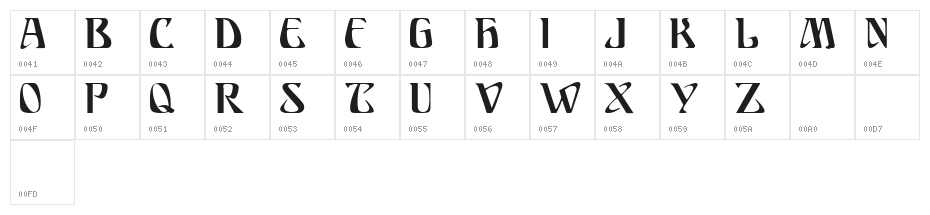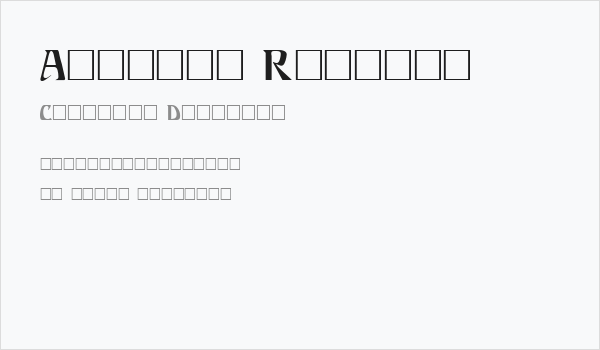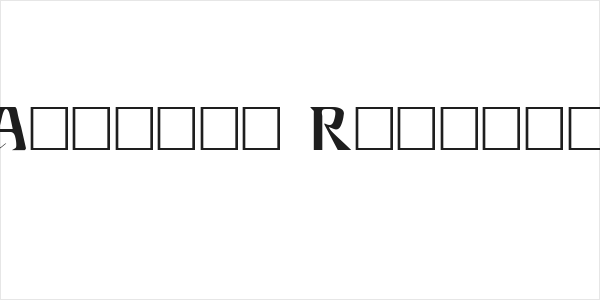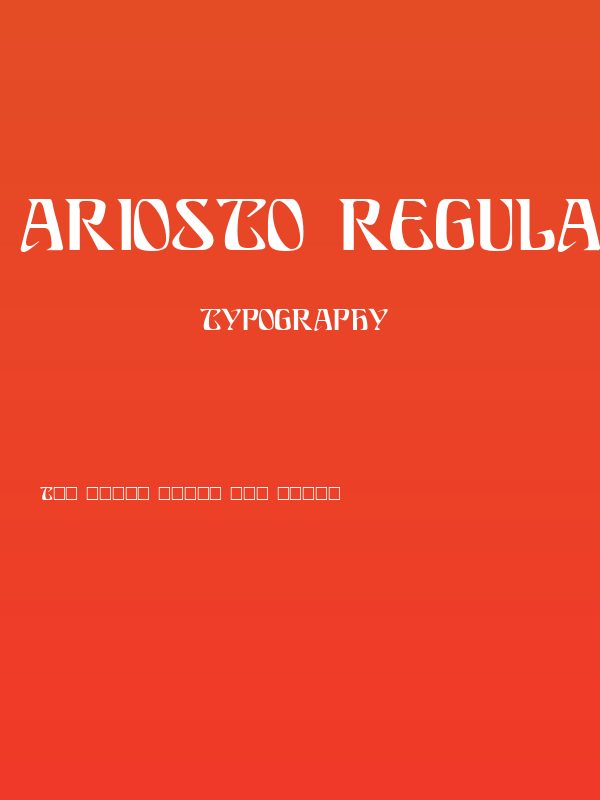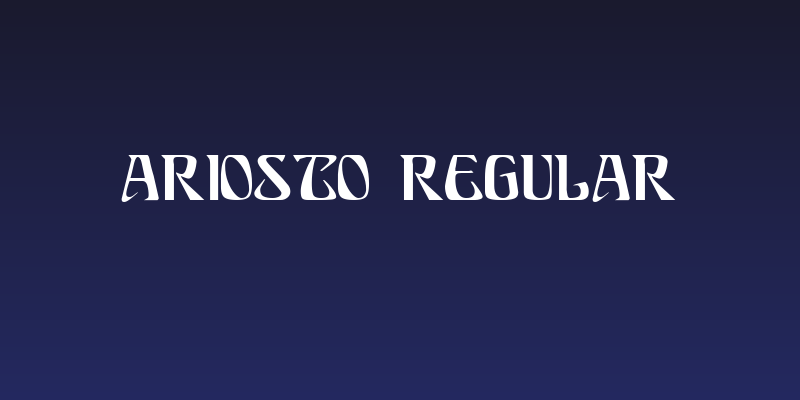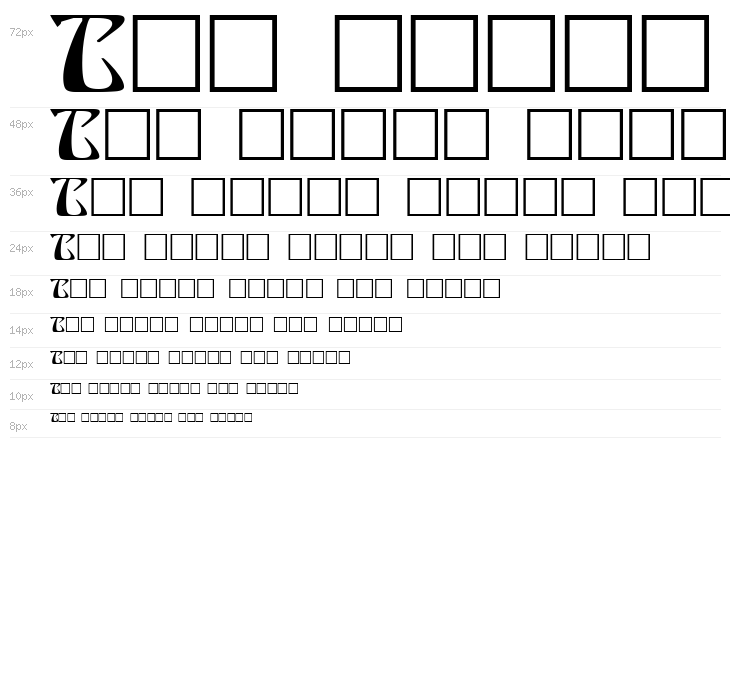
Ariosto Regular Font
✎ Capitals
| Progetti proposti | This font is perfect for projects that require a strong visual impact, such as posters, logos, branding materials, and editorial design. Its bold style makes it suitable for modern and artistic themes. |